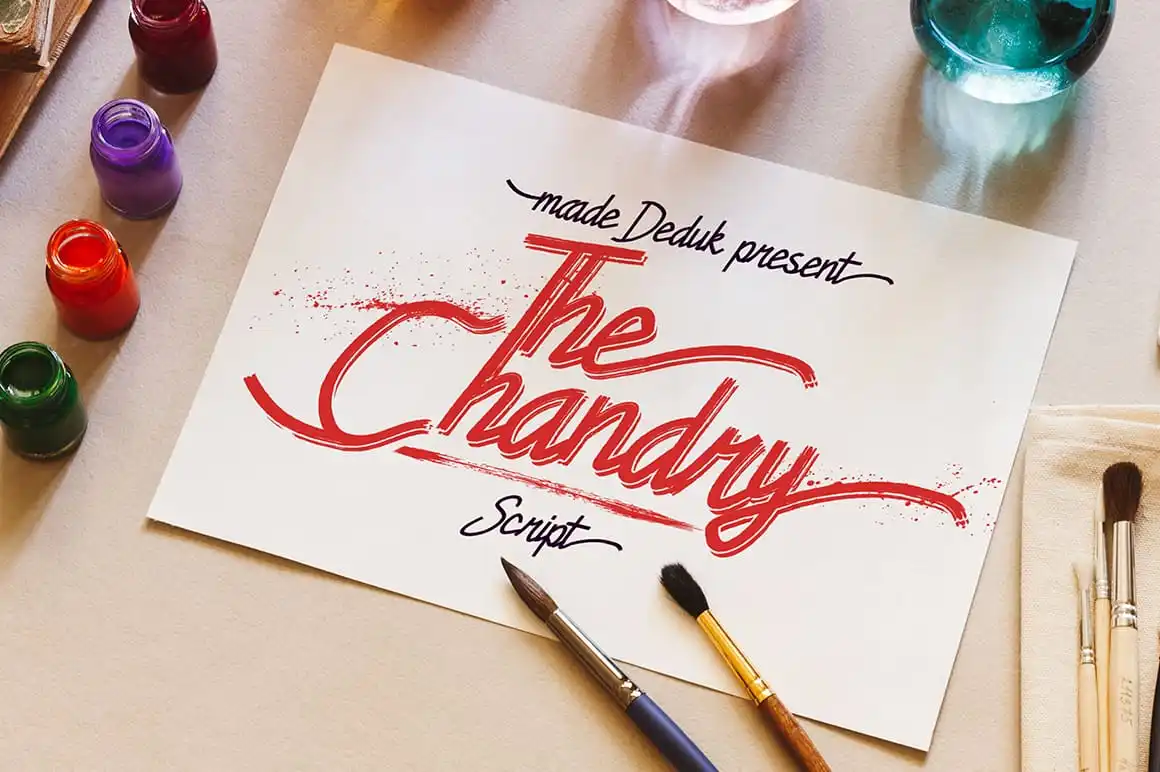
Chandry Fonts – Download Grátis
A Chandry é uma fonte de tipo vintage inspirada nos estilos clássico e antiguidade. Suavemente revigorante, essa fonte traz à tona a essência do design gráfico antigo sem perder seu charme moderno. Perfeita para qualquer aplicação, seja ela branding, embalagem de produto, convite ou mesmo até mesmo um poster publicitário, a Chandry oferece uma experiência visual única e imediata que captura o público com sua elegância vintage. Feita pelo designer madeDeduk, esta fonte é um ótimo complemento para qualquer projeto que busque trazer estilo e personalidade à sua marca ou design.